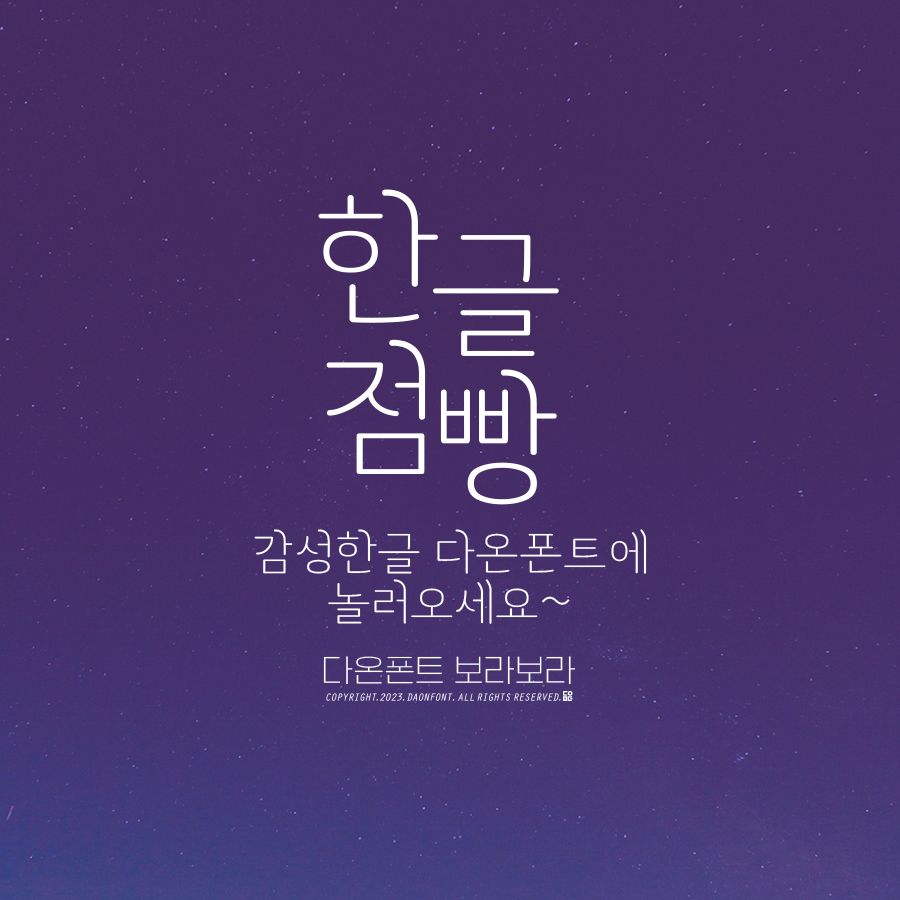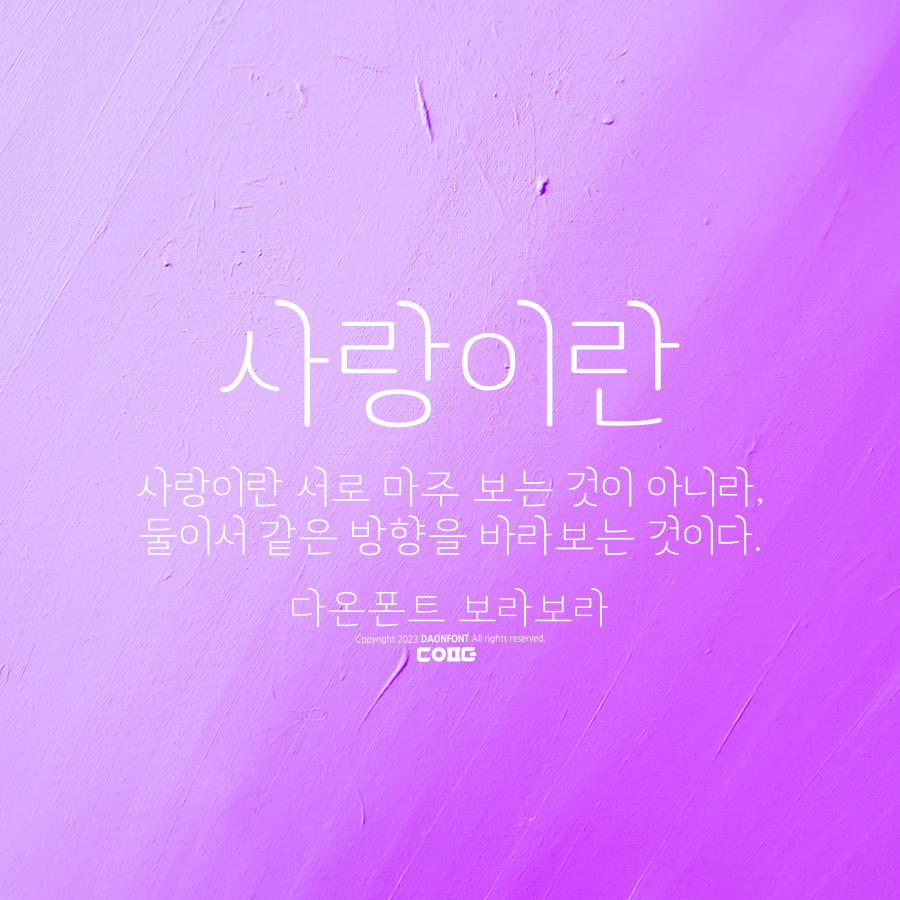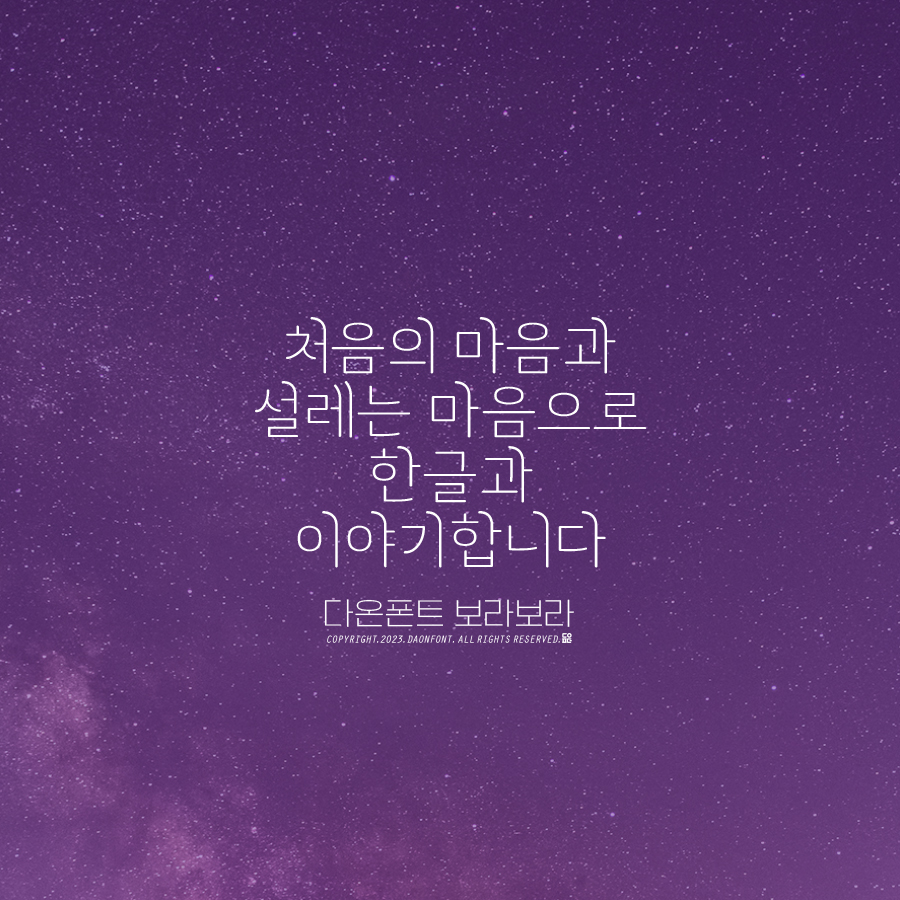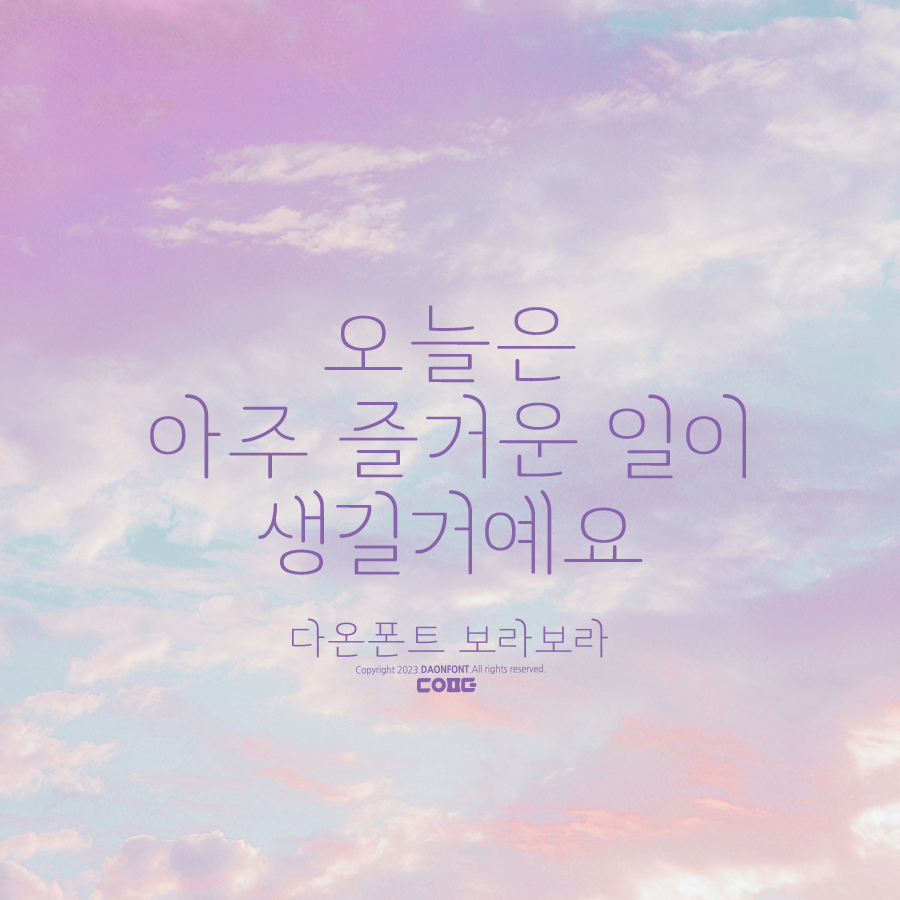
5월 신서체 다온폰트 보라보라 출시 안내
다온폰트 5월 두번째 다온폰트 신서체, 다온폰트 보라보라가 출시되었습니다.
초성을 감싼듯한 부드러운 획의 기둥과 자소의 획마감을 둥근 모서리를 가진 보라보라는
부드럽고 차분한 느낌을 가지는 감성적인 카피서체입니다.
감성적인 카피문구에 잘 어울리는 카피형 서체입니다.